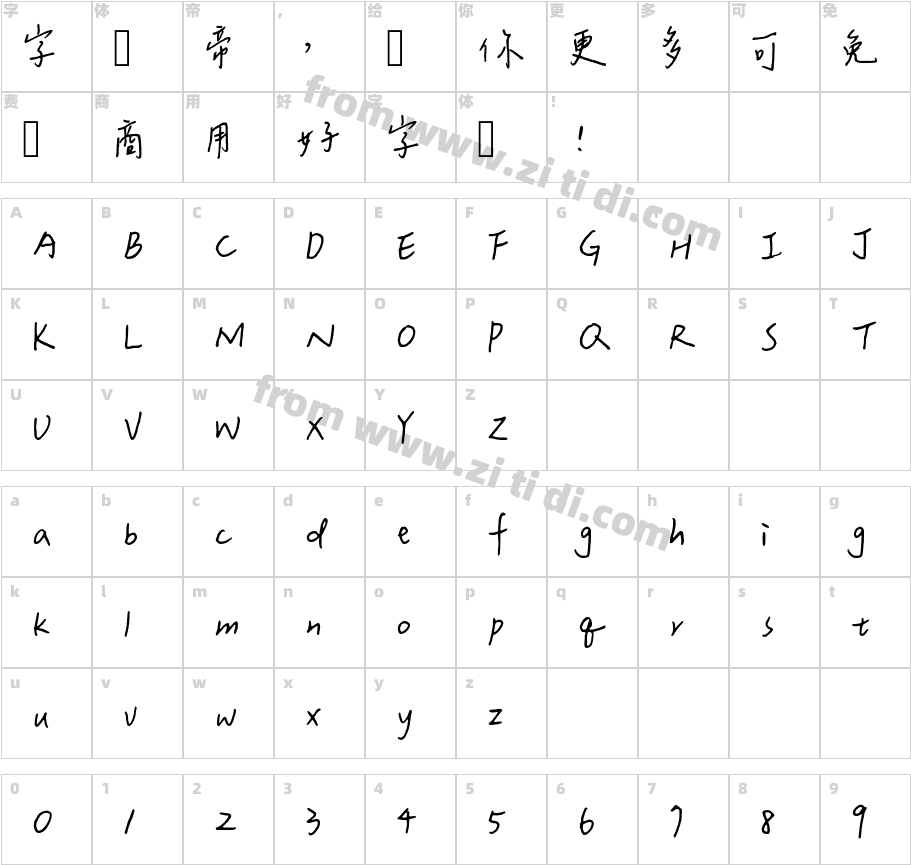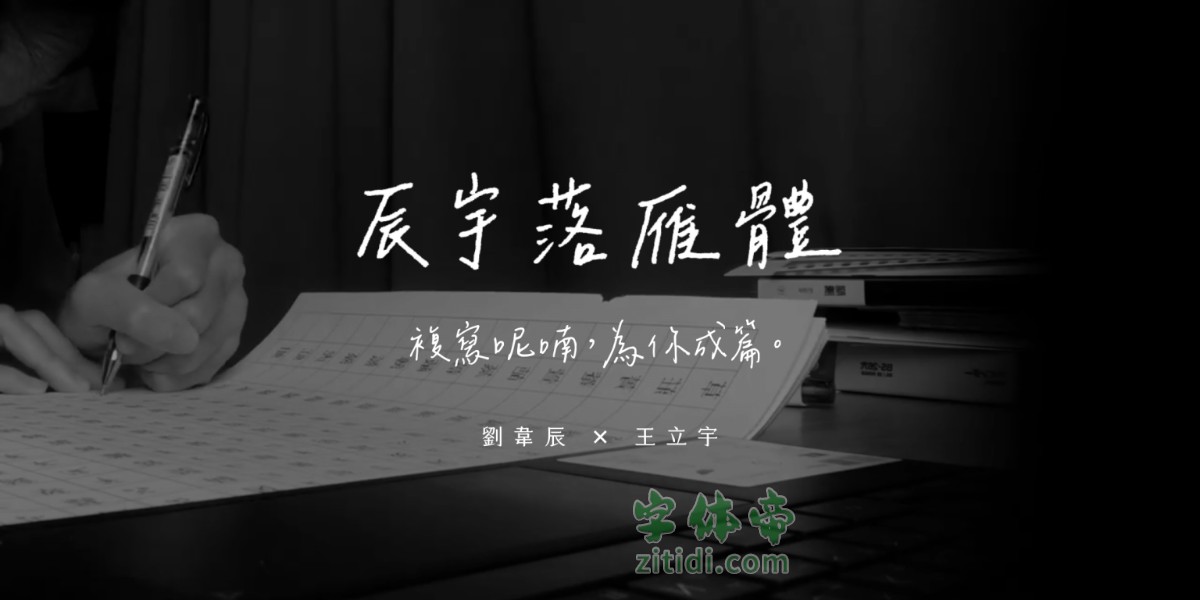
「辰宇落雁体」是我与韦辰在学校的自主学习画册,由韦辰负责我们写作,我进行后制制作。书法字型像是将字复写于纸上,让字迹留下这种近似隼的形式,使被复写的日常化,犹如一种永恒的召唤,在任何可能永无质的以后,也为你书写成篇。
制作故事
欸,你要不要做繁体字?
八月的,那阵子我去年的关注字型相关话题,在偶尔看到韦明星的手稿后也,萌生出的自己能做字体字体,真是太酷了而适逢逢108课纲的,课纲强调自主的精神,让我们有机会发展计画,于是,我们学习手工巧的钻研之路就这样开始了⋯⋯
「万事开头难」开始起步但并没有这么顺利,对于这个字型的我们来说,寻找相关信息,忽地而出,YouTube「频道加壹线」与刚刚字体的字体,我们需要请手写字型的制作过程,获得他们指导的真诚的回覆,并给我们展示了我们在制作字型的过程中的重要提示,我们的同事计算了向我们分享了与我们的画图技术交流的过程。
我们最初是字型制作平台──「守字网站」习上得手写字型的制作流程,后来为了进一步的制作自由,我们尝试破解拆解流程,并以自己的方式进行制作,摸摸摸索的过程并非一蹴及人窝制作,韦氏的每周一期的字体,我钻心研究的同时研究的明星就在书本上写着,旁人在潜行的过程中,为心中的理想和肩负着,是枯竭着的,日复一日的写法,现在、修改后的设想,我们还是挺浪漫的,为了与理想的完成,不惜人性的绕点,也有好几次气喘吁吁的想着,好像真的没有出来了,是对于成果的想像才让我们继续下来。
在字体配方中逐渐获得好评,过程中取得成果时也取得了第一次奇迹般的成果,却在第一次取得了惊人的成果,我们在成功的时候,也成功打出了第一次的成果,受到了感动。手写字体这件事,似将字词复写于纸上,将字迹留下为人使用。
回想制作的契机,那句“欸,你要不要做手写字体?”在今天最后她实现了,韦辰与下文字后也将在十六岁告别,正字如其人,未来回首,自己能在字里行间看到。
其他可能
其实,我们在简单的一开始制作的作品是因为 Pentel Touch 的字体迟到了,但因为创作目标与调整字体,在纸稿完成后,迟迟未能释出字型。而稿我们也同时创作制作也是原子笔书写的版本,现在的「辰宇落雁体Thin」。